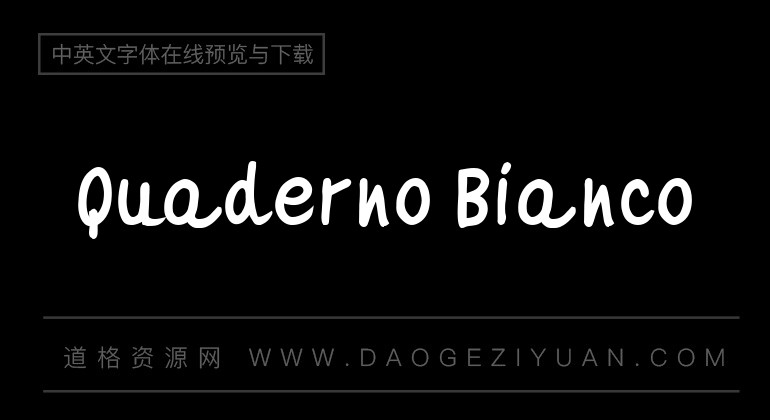
Quaderno Bianco
Quaderno Bianco是一款美式手写体字体,由意大利设计师Alessandro Segalini设计,于2020年发布。该字体以简单明快的笔画构成,具有温和的色调,可以在印刷和网页上使用。它可以用于各种文档,如商业文档、报告、广告、宣传册等。此外,Quaderno Bianco字体也可以用于标签、书籍封面、海报和其他设计作品。
Quaderno Bianco是一款非常不错的手写艺术字体,具有很好的视觉感,适合于文化类的宣传设计、商业类品牌的广告和产品包装设计以及个性化文字排版等较多场景。